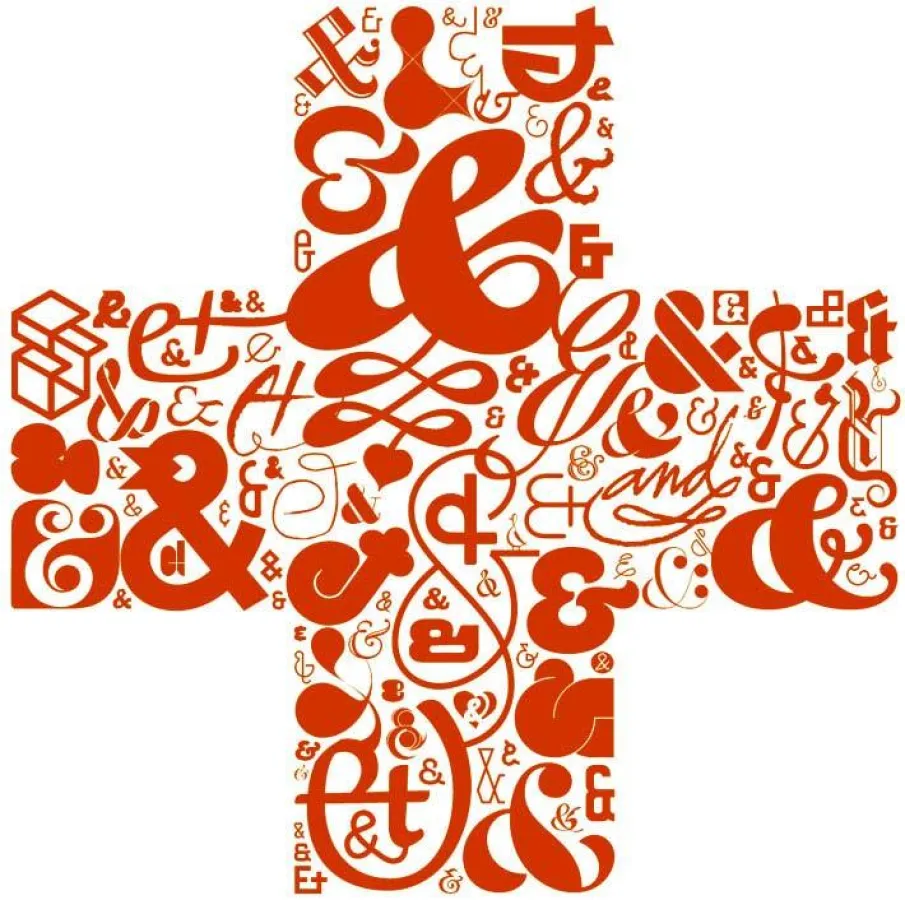
(openPR) Berlin, 18. Februar 2010: Die typografische Gemeinschaft ist dem Ruf der Society of Typographic Aficionados gefolgt und hat eine Schrift mit dem Titel “Coming Together” entwickelt. Coming together ist ein OpenType Font, bestehend aus über 400 Plus-Zeichen, designt von Schriftdesignern, Grafikdesignern und anderen Kreativen aus 38 Ländern.
Das Plus-Zeichen drückt die Verbundenheit mit den Erdbeben-Betroffenen in Haiti aus.